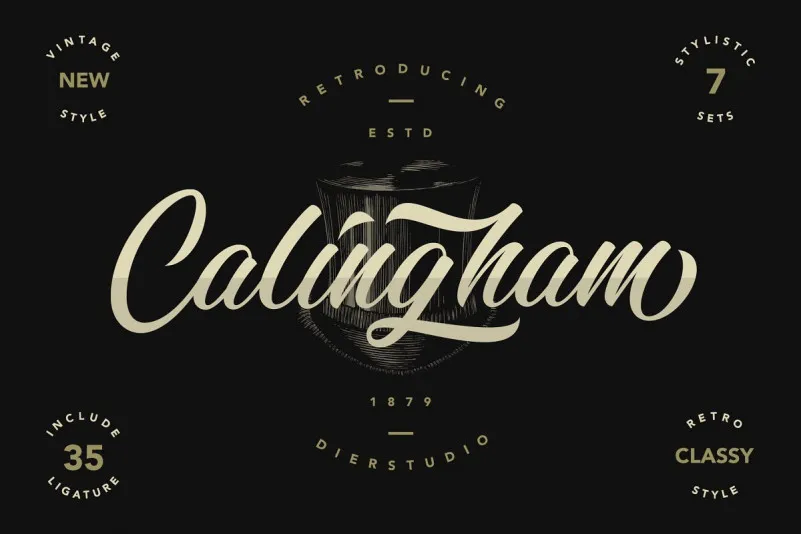
Calingham Calligraphy Font – Download Grátis
Bem-vindo novamente ao mundo da tipografia! Estamos encantados com a introdução da Calingham Font. Esta elegante e feminina fonte é perfeita para qualquer projeto gráfico que deseje um toque sofisticado e vintage. Criada pelo Dierstudio, esta fonte contém incríveis saltos de letra que adicionam um brilho natural ao seu design. Ideal para aplicar em tudo desde logotipos e postagens nas redes sociais até embalagens de produtos e materiais de escritório. A Calingham é uma brush type, caracterizada por sua elegância clássica e estilo vintage retro que ainda consegue capturar o toque refinado que você está procurando em suas criações. Seja para personalizar seu produto ou estilizar seus posts do Instagram, a Calingham Font será um atalho perfeito em qualquer projeto!